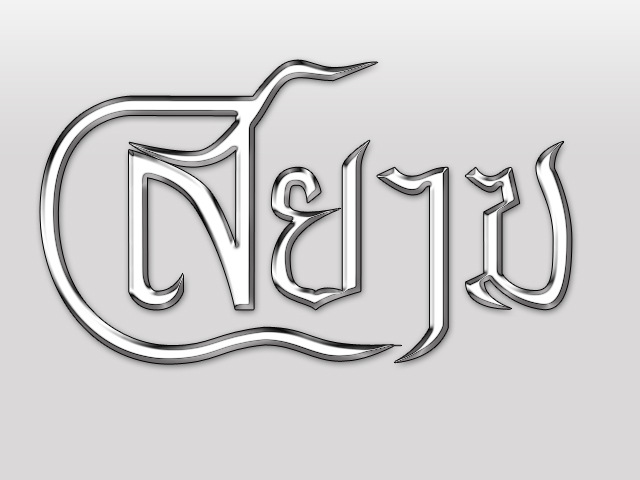
มือใหม่หัดทำฟร้อน
เพิ่งหัดลองออกแบบเป็นครั้งแรกน่ะคับ ยังไงก็ฝากเนื้อฝากตัวด้วยน่ะคร้าบบบบ
อ้อ อันนี้ใช้ pen tool ในโฟโต้ช็อปทำน่ะคับ กำลังหาโปรแกรมทำฟร้อนมาใช้อยู่ T T
โอ้วววว
สวยจัดครับ
ม.ม้า หัวแตก เวลาอยู่เดี่ยวๆจะนึกว่าเป็น ฆ.ระฆัง ได้นะครับ
สวยงามครับ
แต่ปรับสระอากับม.ม้าหน่อยก็ดีครับ ป้องกันคนเข้าใจผิด
ว่าแต่สวยงามจัง :25:
ฟอนต์สวยดีค่ะ
แต่ระวังว่า ถ้า ส เสือหางยาวขนาดนั้น เมื่อพิมพ์ร่วมกับสระล่าง เช่นคำว่า สุข สระอุจะไปอยู่ตรงไหน
เพราะถ้าสระอุอยู่ต่ำมาก สระอุของอักษรตัวอื่นๆที่ไม่มีหางก็จะยิ่งต่ำจนห่างเกินไปค่ะ
ฟอนต์แรก
สวยค่ะ
ส เสือ ออกแบบได้สวยดีครับ แต่อย่างข้างบนว่าน่ะครับ  เวลาเอาไปผสมกันตัวอื่นจะยุ่งยากครับ
ส่วนเรื่องหัว ม.ม้า ตอนแรกคือผมกะจะให้เข้ากับหัวของสระอา ที่อยู่ข้างหน้า ไป ๆ มา ๆ เลยกลายเป็นอ่านยากไปเลย T T